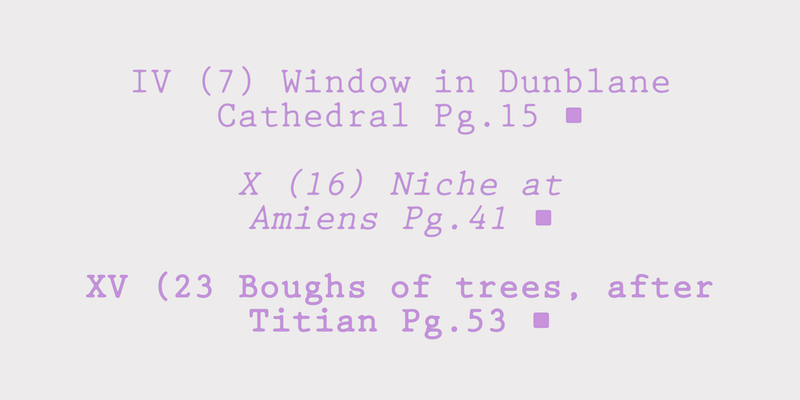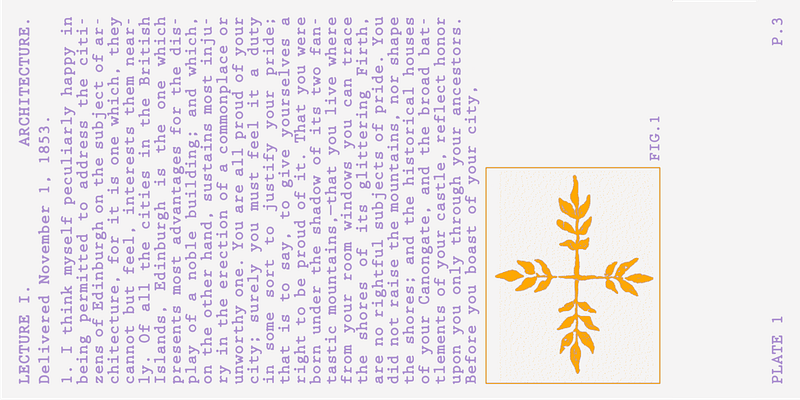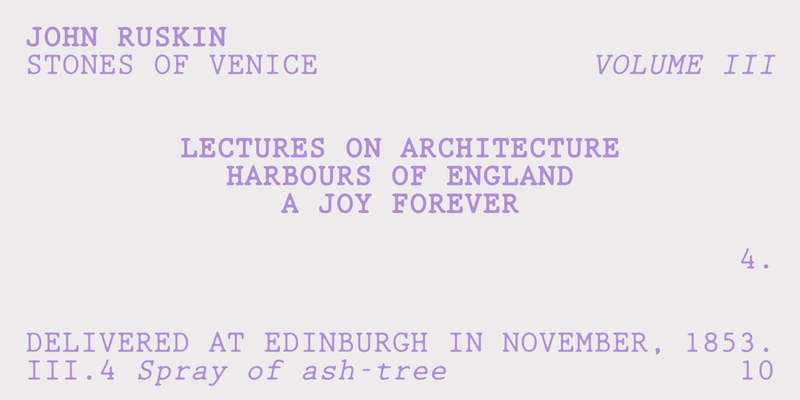
Prestige Elite es un tipo de letra Slab Serif monoespaciada, originalmente pensada para su uso en máquinas de escribir. Fue diseñada en 1953 por Howard Kettler para IBM. Prestige Elite es una buena opción para listas de precios, material tabular y correspondencia de oficina informal. Los tipos de letra que se diseñaron originalmente como tipos monoespaciados para máquinas de escribir son eficaces en materiales para la comunicación personal o para capturar el aspecto y la sensación de tiempos pasados.